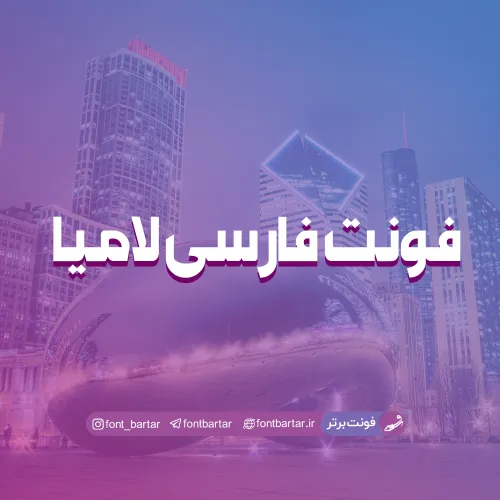
فونت فارسی لامیا
این فونت در دسته فونت های فارسی قرار داردفونت زیبا و جدید لامیا با چینش استاندارد و تقریبا هم سبک فونت فارسی تیتر مناسب استفاده در تایل کارها و همچنین مناسب مصارف عمومی هم اکنون بصورت رایگان از فونت برتر در دسترس است.